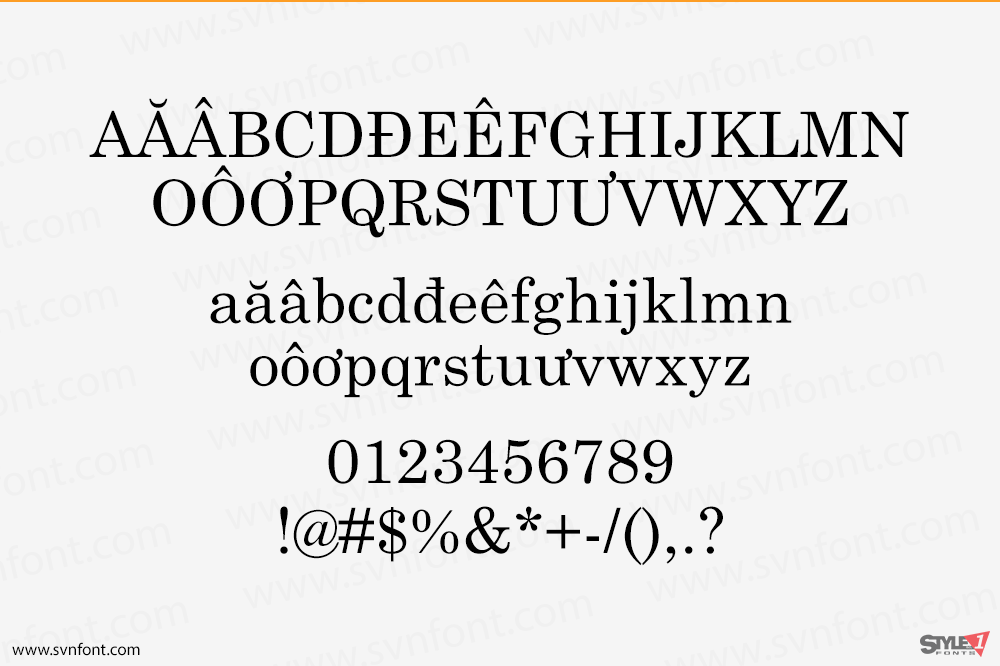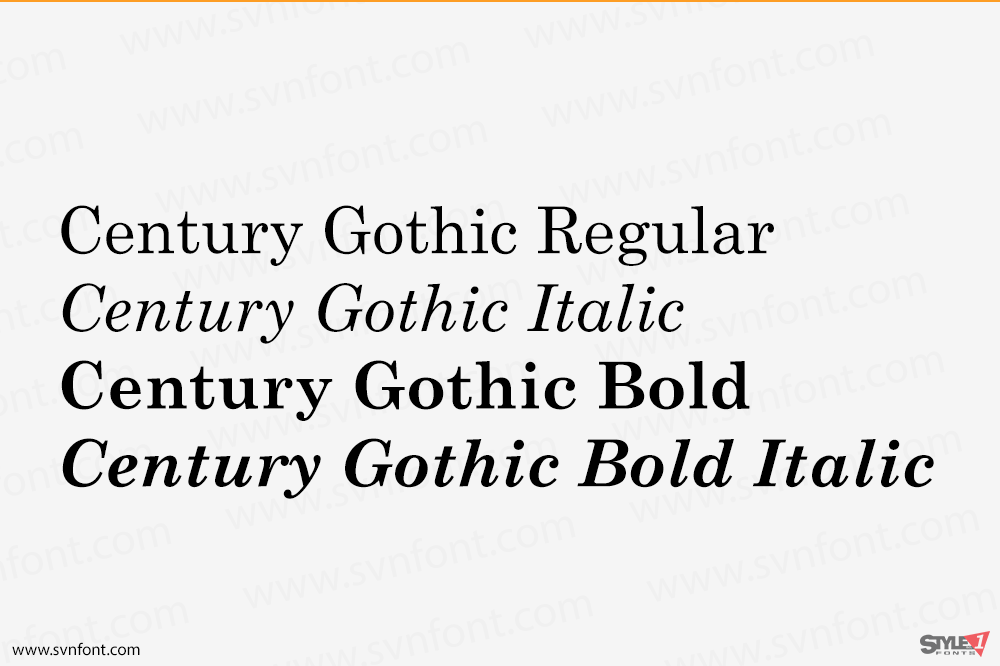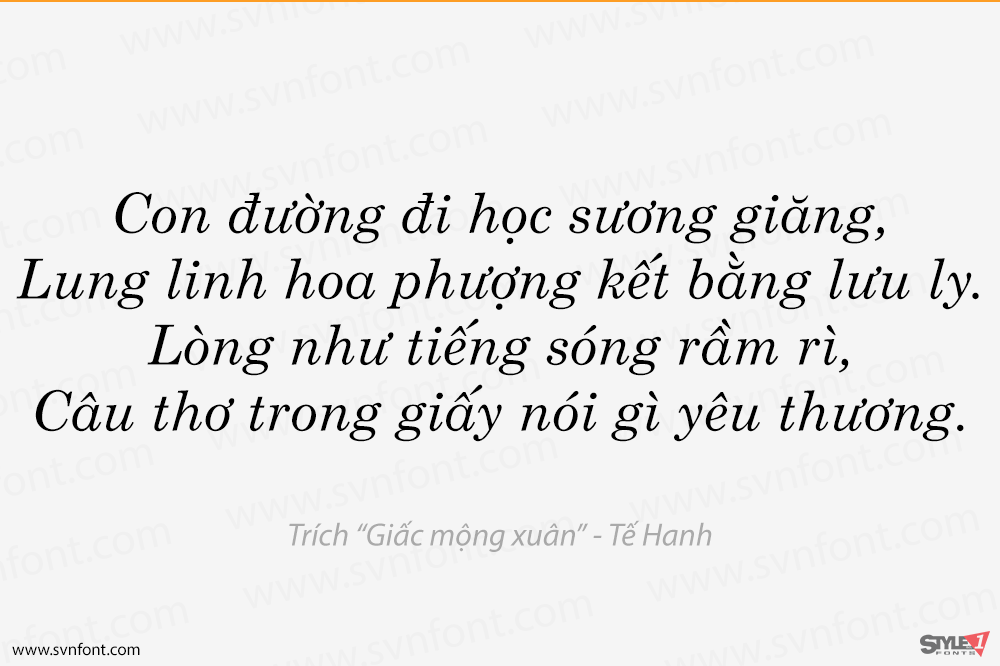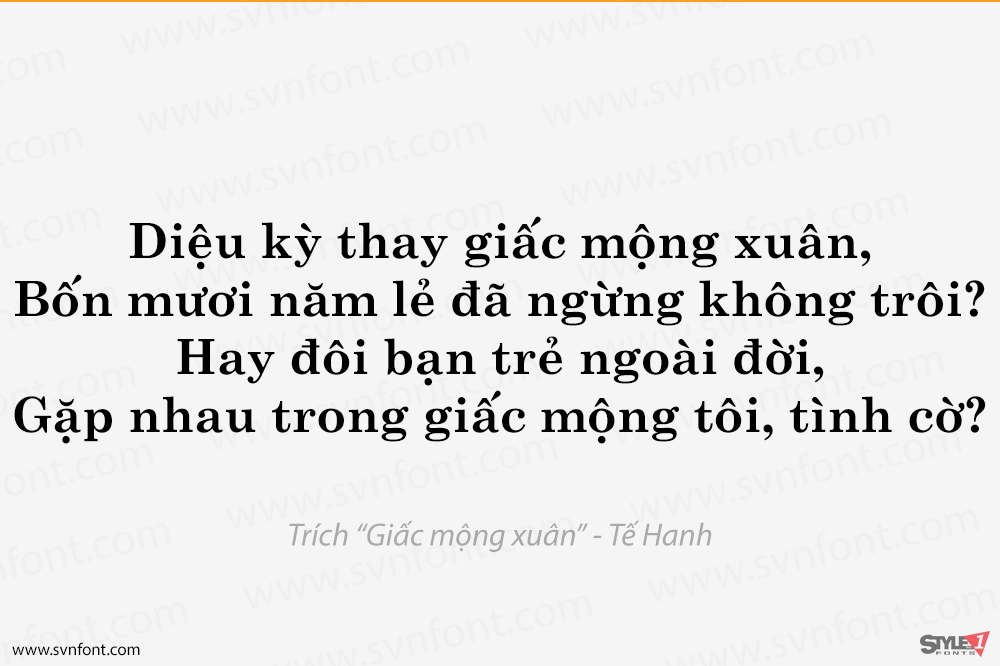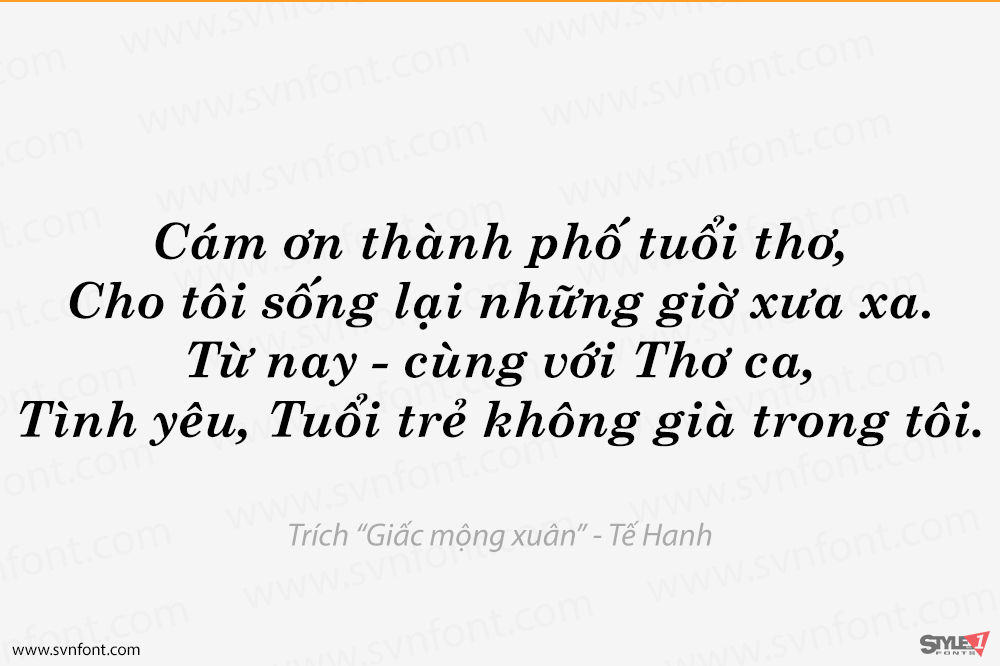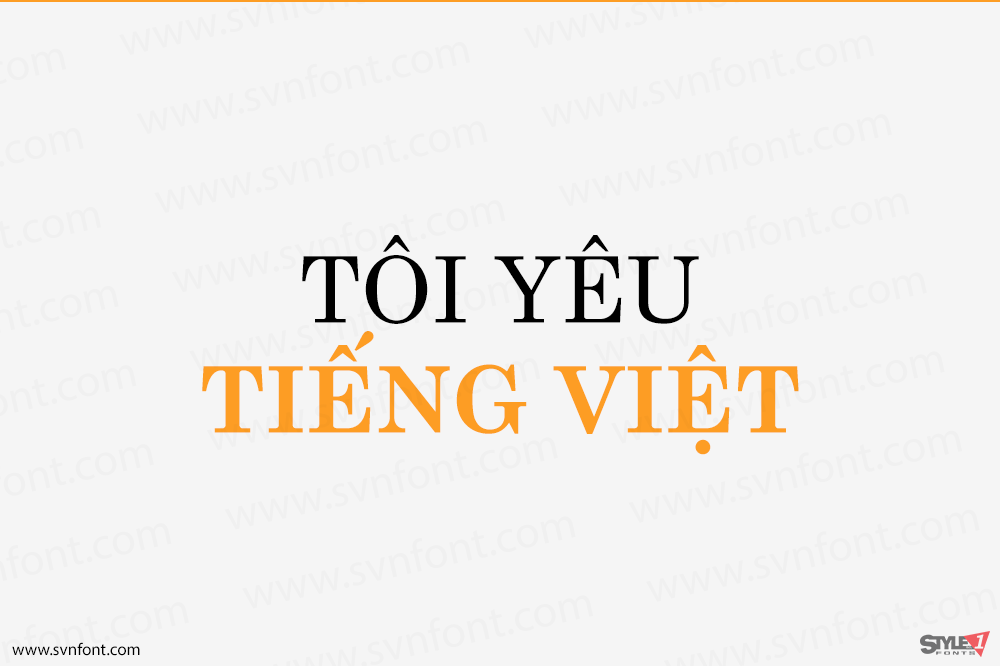
Monotype Century Schoolbook là một thành viên khác của họ Century, dựa trên kiểu chữ Century Expanded. Họ font Monotype Century Schoolbook được thiết kế để đáp ứng nhu cầu về một kiểu chữ vững chắc, dễ đọc cho việc in sách giáo khoa. Nó rộng hơn và nặng hơn Century Expanded, đồng thời cũng có ít độ tương phản hơn giữa các nét dày và mỏng.
Được Monotype cắt lần đầu tiên vào năm 1934 và dựa trên các phiên bản từ ATF và Lanston Monotype, bản chất bền vững của Monotype Century Schoolbook, cùng với khả năng dễ đọc vốn có của nó, đã khiến nó trở thành lựa chọn phổ biến để sắp chữ cho sách, báo và tạp chí.
Nhà thiết kế: Monotype Studio, Morris Fuller Benton